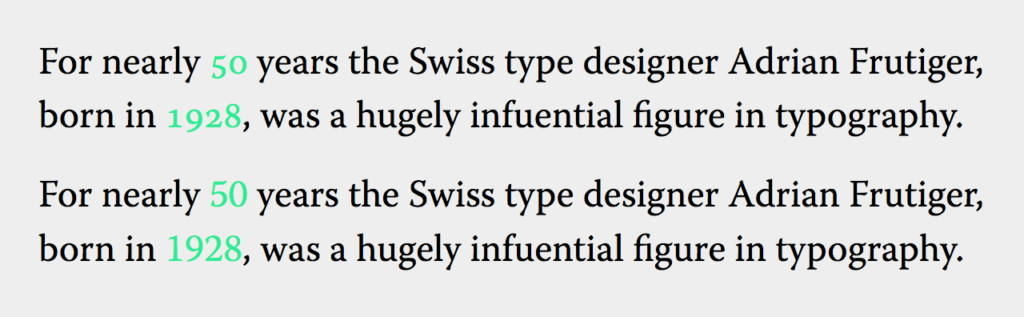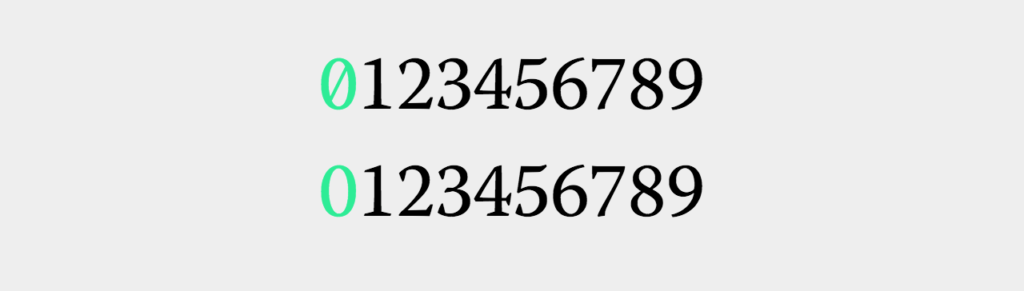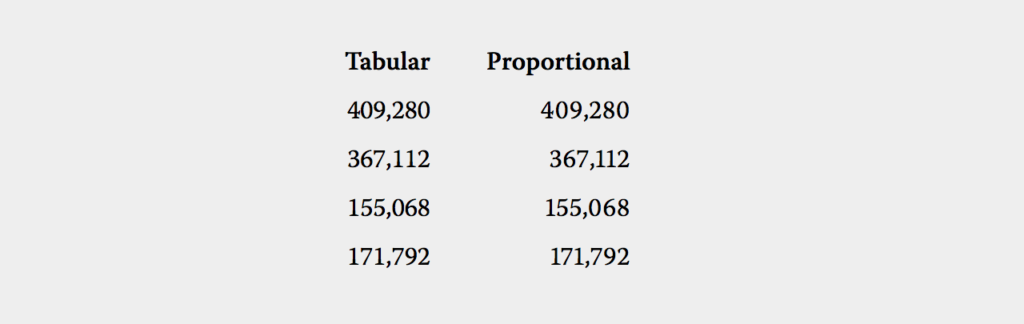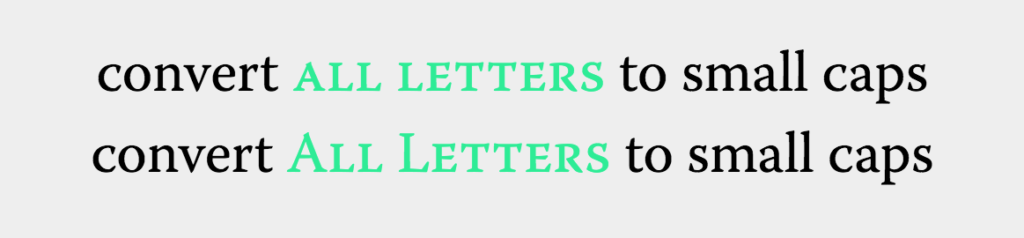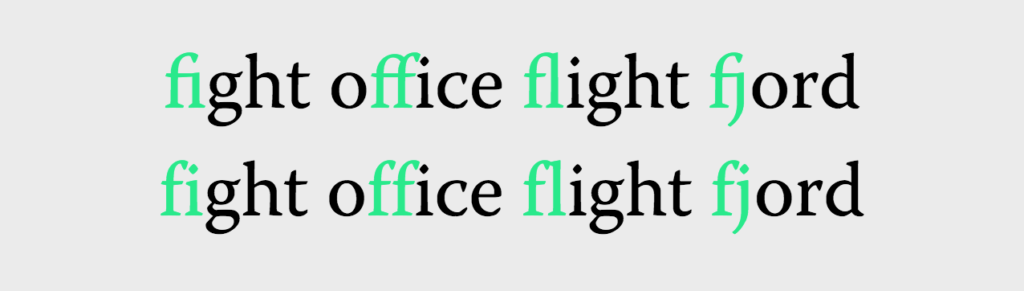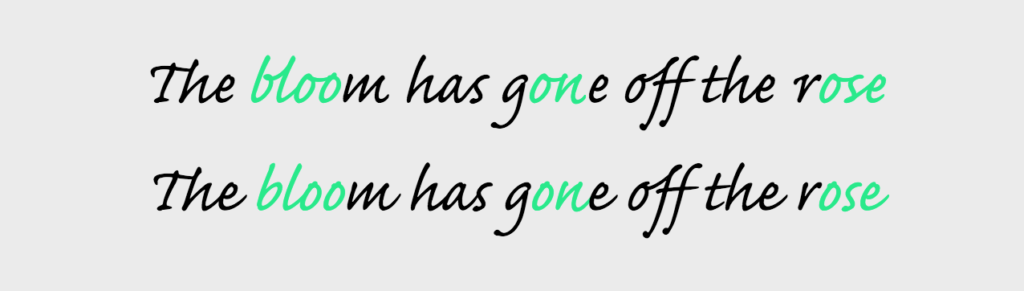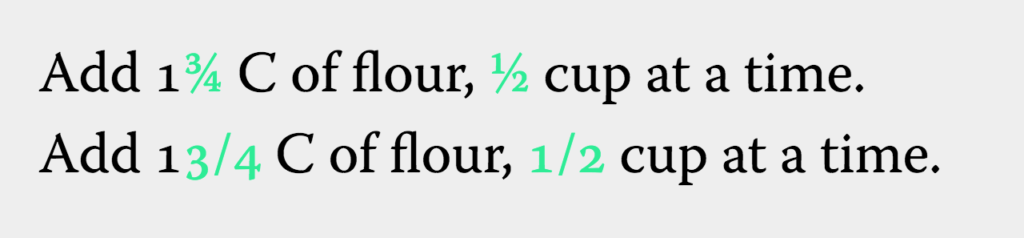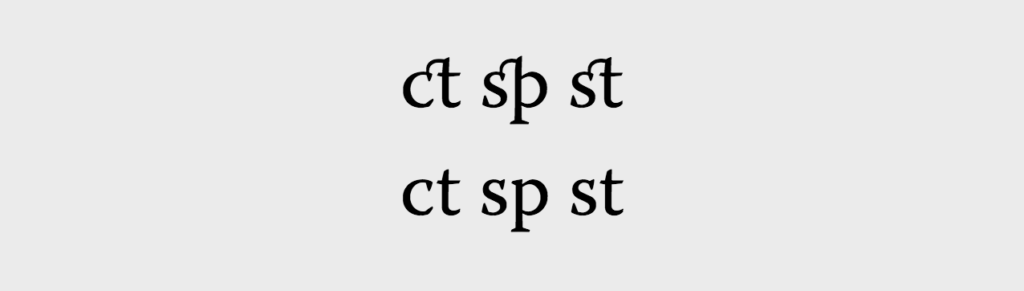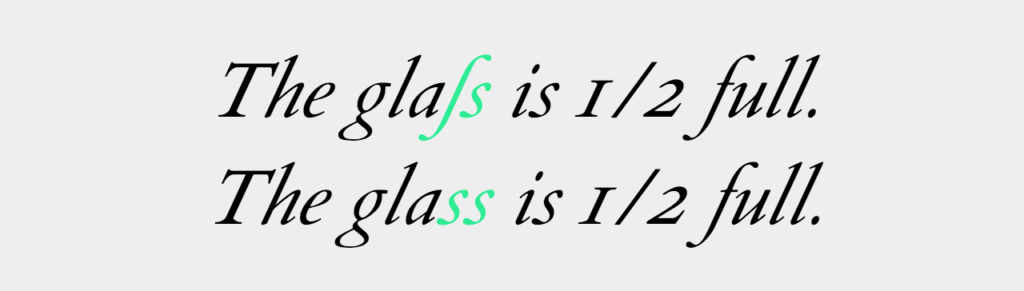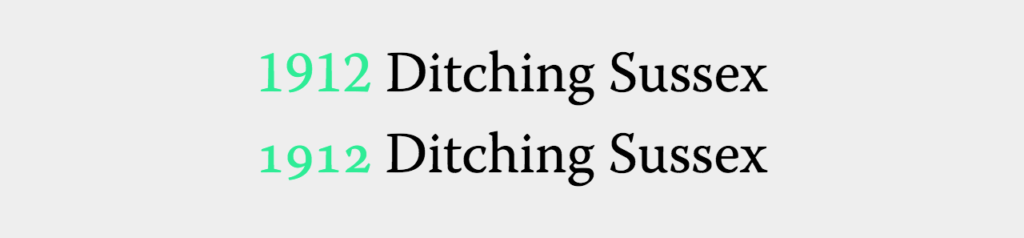
字体变体font-variation-*
今天在Twitter看到Codepen上的一个示例,感觉很神奇。刚开始以为是用了什么黑科技,但仔细一看是纯CSS实现的一个效果。示例中最关键的是使用了font-variation-settings
属性。那么这个属性有什么神奇之处呢?容当后述。
在详细介绍font-variation-settings
属性之前,先把Demo效果给大家看看:
如果要用一个词来描述的话,可以把其称为字体变体(Font variants),对应的CSS属性就是font-variation-*
属性,其包括连接(ligatures)、大写(caps)、数字(numerals)和替代字形(alternate glyphs)。这些属性可以让我们在Web上创建更精准、更漂亮的排版(文本)效果。
事实上,Web上的排版总是要落后于它在它印刷中的效果。但这是可以理解的,因为打印在页面上的字体已经经过几个世纪的发展,可以说发展到一个复杂的程度。而在浏览器要达到这样的一个层次,还是很难的。
但是,由于Web字体中OpenType功有的增加,以及CSS特性的完善与能力的提高,Web上排版和印刷上排版之间的差距在逐渐拉小。
那么今天这篇文章,借助前面的示例,我们来看看如何使用CSS控制OpenType特性,但请记住,你所使用的任何Web字体需要支持这些特性。
font-variant-*
属性
在CSS中可以通过font-variant-*
属性来控制大多数OpenType特性。也可以使用font-feature-settings
用来支持低版本浏览器。然而,只要可能,你应该使用更现代的font-variant-*
属性。在实际使用的时候,可以使用@supports
规则来对font-variant-*
做降级处理,对于支持的浏览器使用该属性,不支持的浏览器使用font-feature-settings
。
可能到现在为止,你和我一样,都还不太明白上面的代码究竟起了什么作用。别担心,继续往后阅读,你会整明白的。
font-variant-*
主要包括:
font-variant-ligatures
font-variant-caps
font-variant-numeric
font-variant-alternates
font-variant-east-asian
后面的内容简单的来看看这些属性。
font-variant-ligatures
连接是由两个或两个以上的字答组成的单个字形。它们通常能防止难看或尴尬的字母碰撞。主要是功能是有助于辨认。
font-variant-ligatures
可以用以下关键词做为其属性值:
common-ligatures
这些连接是设计者决定在正常情况下使用的连接。在大多数情况下,应该使用这些,因为大数浏览器都默认启用它们。
最常见的连接值是fi
、ffi
、th
或者类似的。它们对应的OpenType值为liga
和clig
。两个值都是有可能的:
common-ligatures
:激活连接no-common-ligatures
:禁用连接
比如:
效果如下:
上一行开启连接,下一行禁用连接的效果
discretionary-ligatures
这些可以用于印刷方面的连接,可以达到特殊效果。这些默认是禁用的。也可以理解为,这些值可以用来控制特定的连接,指定的字体并由OpenType设计器来定义。它们对应的是OpenType值dig
。它也有两个可能的值:
discretionary-ligatures
:激活连接no-discretionary-ligatures
:禁用连接
如果你的代码中设置了:
效果如下:
第一行开启连接,第二行禁用连接
contextual
这些值控制字母是否适应它们的上下文。也就是说,它们是否适应周围的字母。这些值对应于OpenType中的calt
。同样的contextual
表示启用;no-contextual
表示禁用。
historical-ligatures
使用这些值,看上去就像德文中的tz
显示成ß
。它对应的OpenType值是hlig
。historical-ligatures
环开启,而no-historical-ligatures
禁用。
font-variant-position
我们经常使用了sub
和sup
元素的来改为字符在垂直方向的位置。默认情况下,浏览器会使用一个常规的数字字符,使font-size
更小,并使用vertical-align
来提高或降低它。这些都不是真正的sub
和sup
,而且通常会显得很难看,更不用说它们会打乱line-height
。
值得庆幸的是,现在有一种方法可以使用font-variant-position
真正实现sub
和sup
这样的效果。不过目前该属性只在Firefox中得到支持。
sub
实现类似于<sub>
标签的下标字符效果:
另外,目前这些属性,浏览器能支持的为数不多,不过不要紧,感兴趣的可以玩玩,体验一下。或者自己把文章开头的示例修改一下下,说不定能达到另外的效果。
需要注意的是,文章开头的示例,还使用了CSS其他的一些属性。这里就不多讲了。